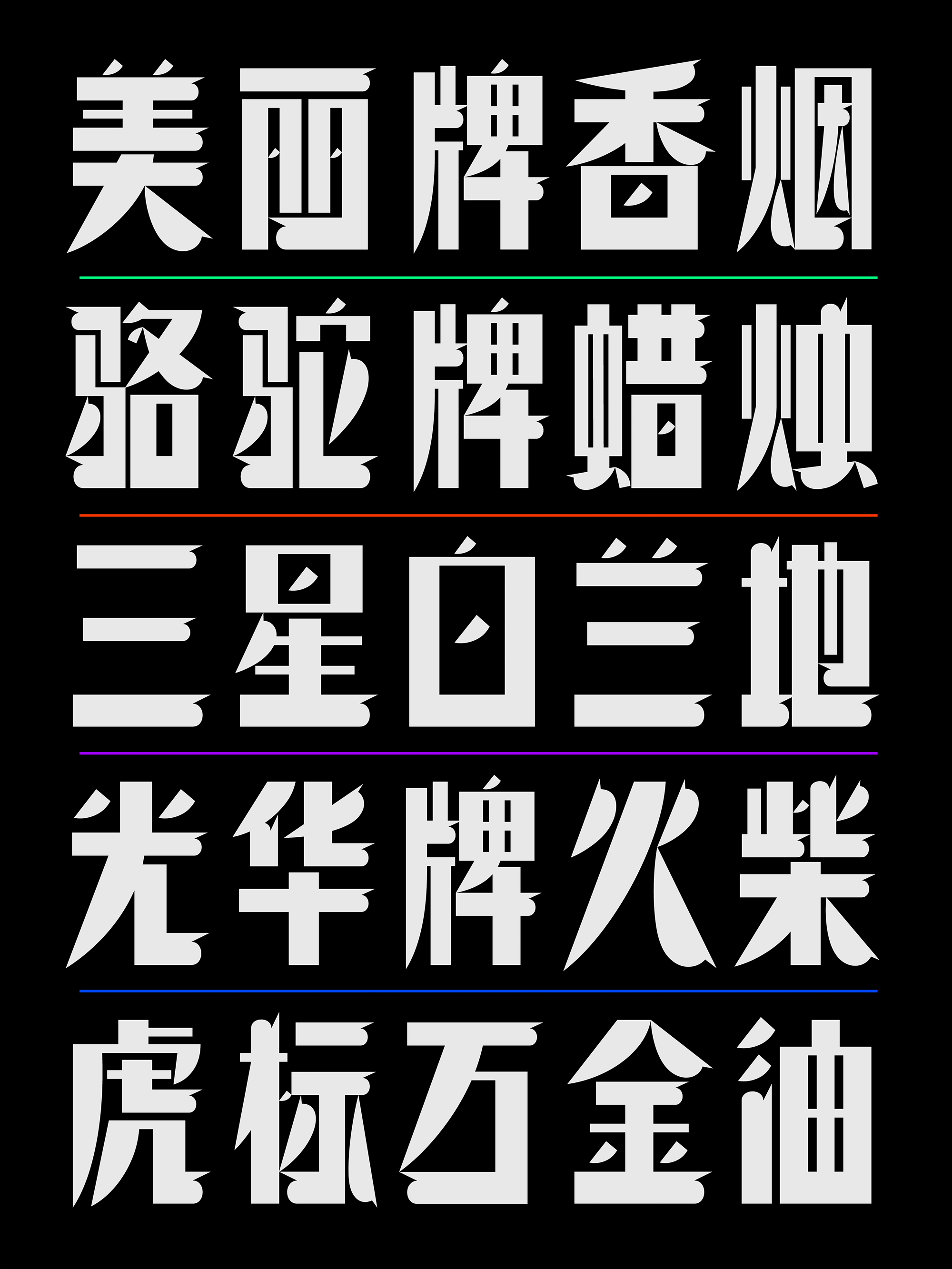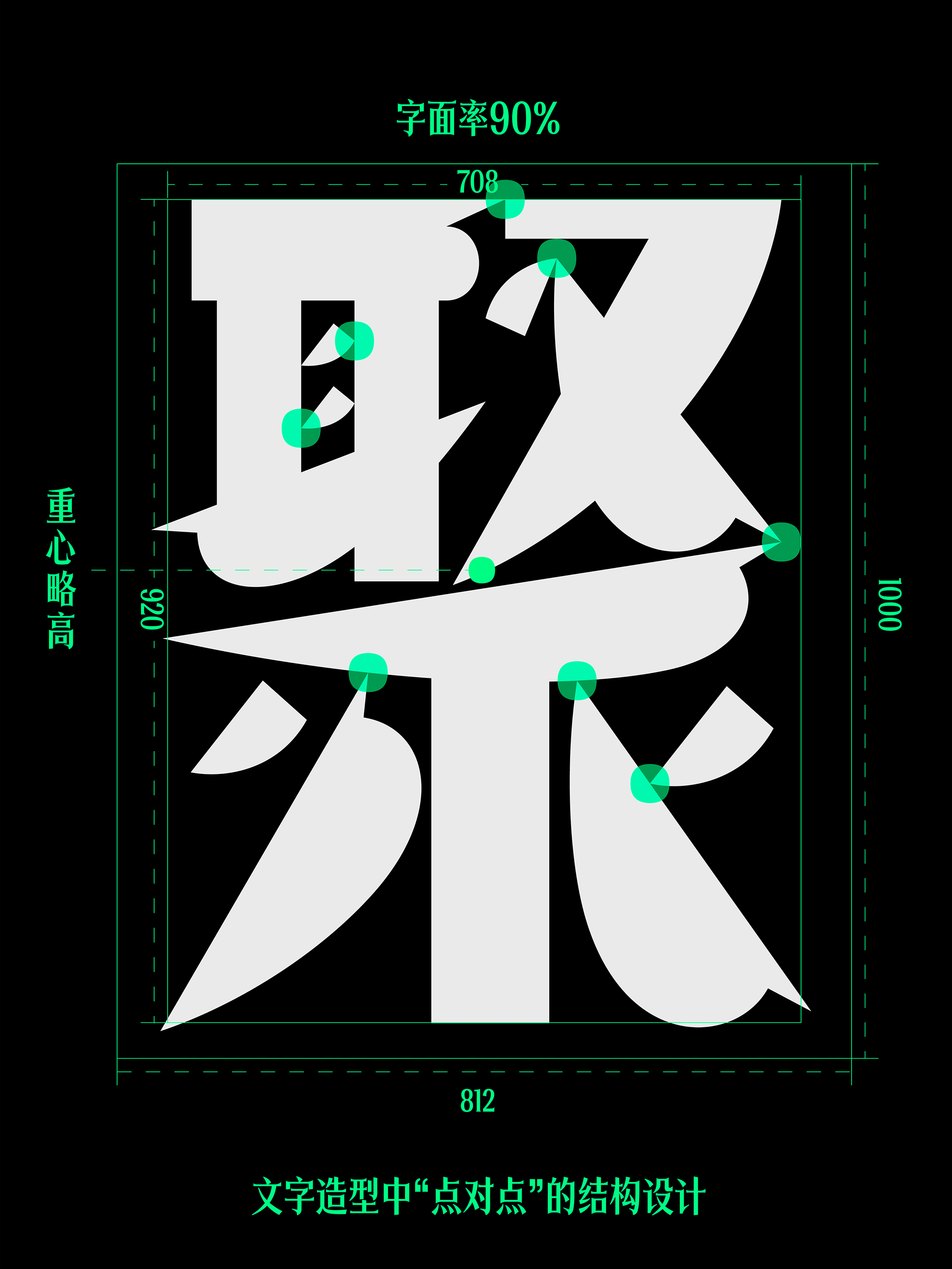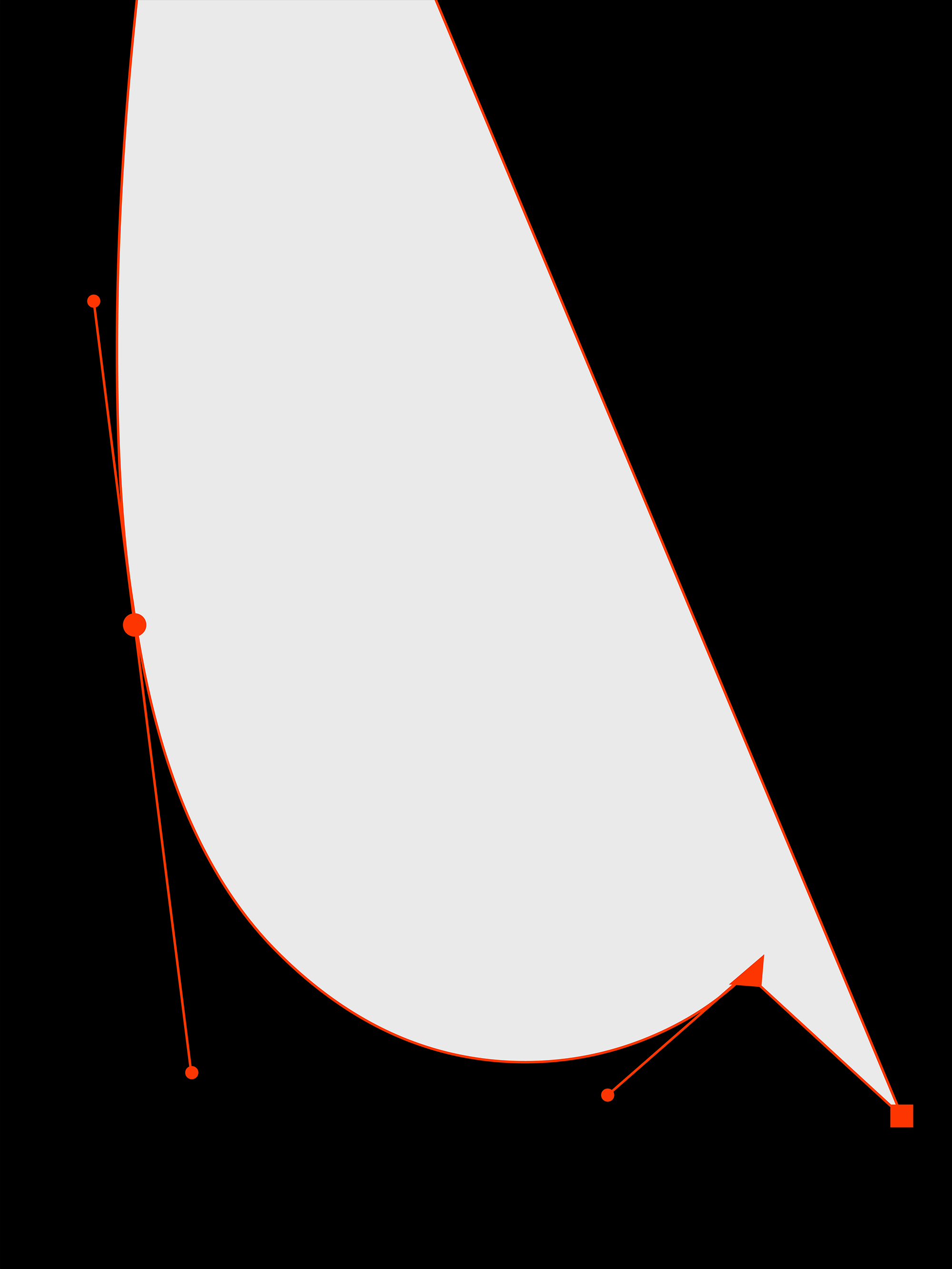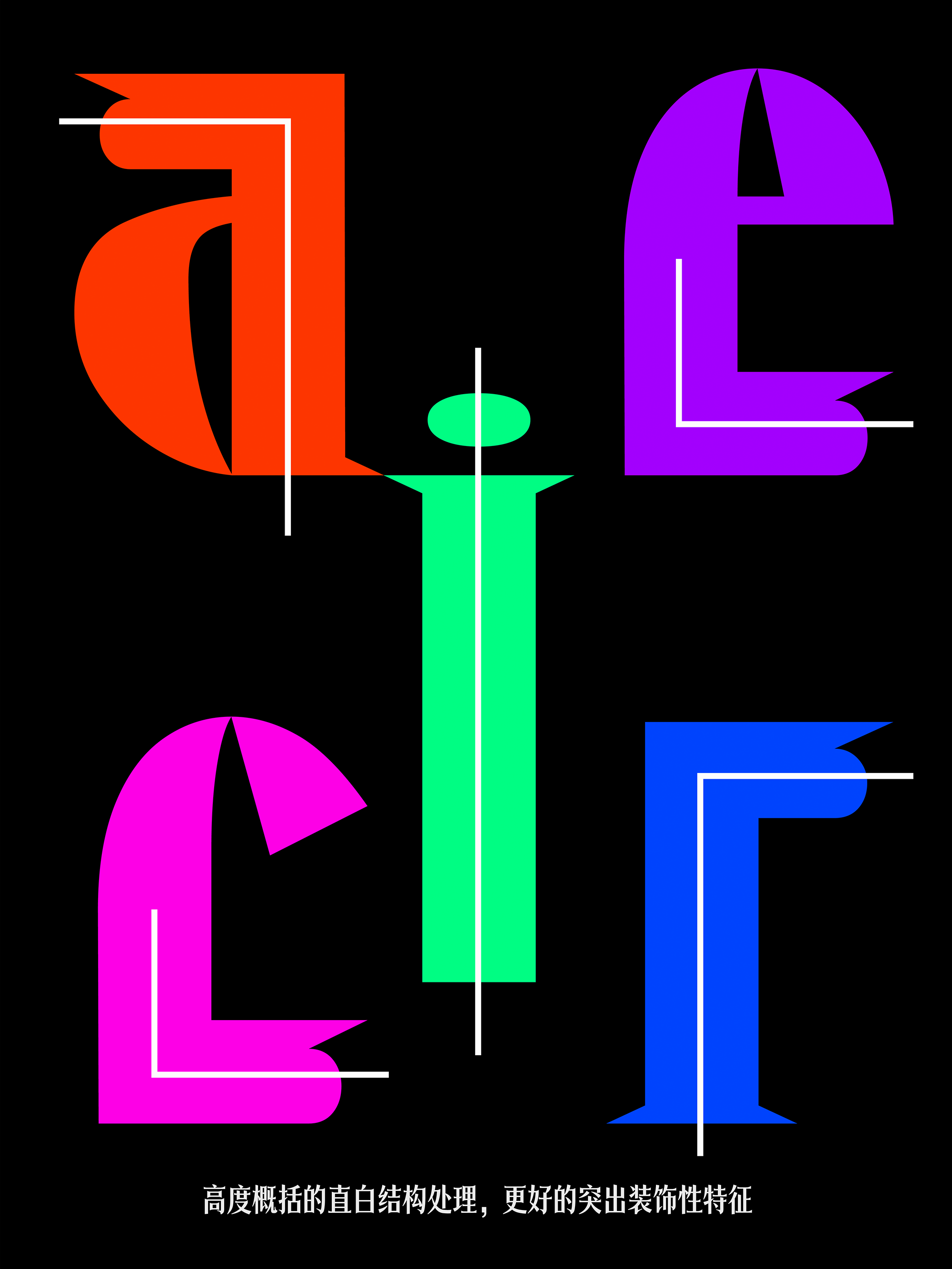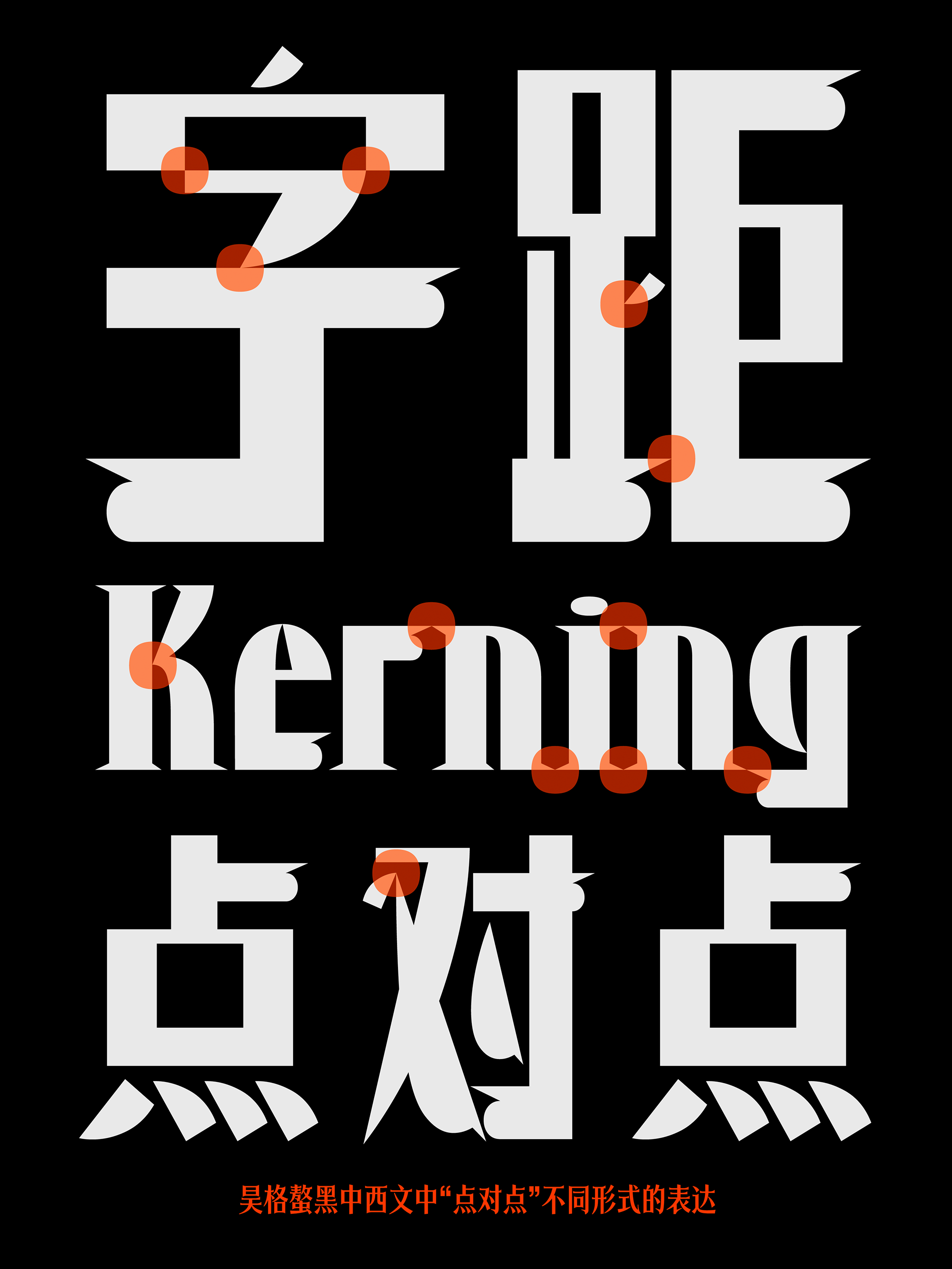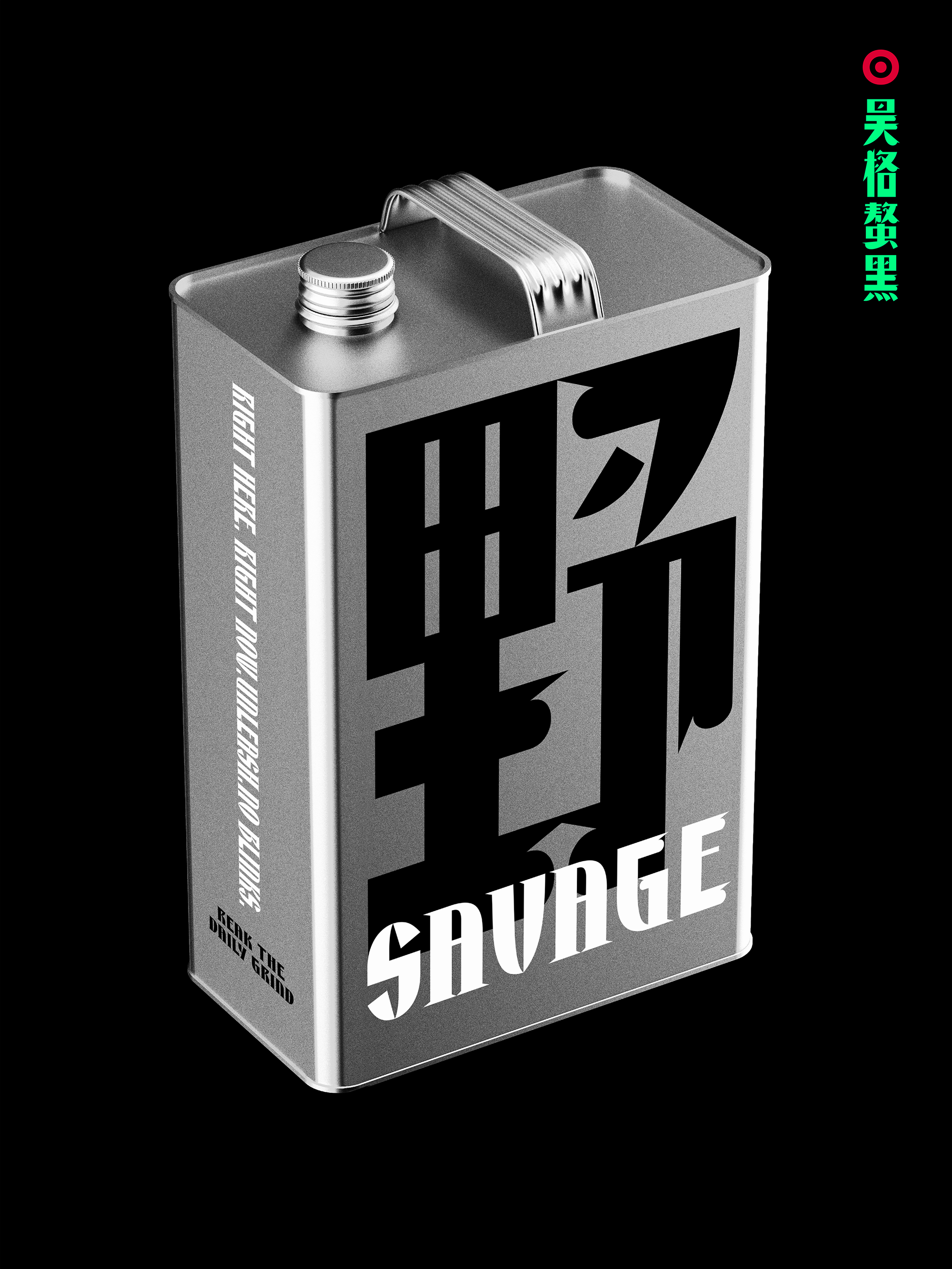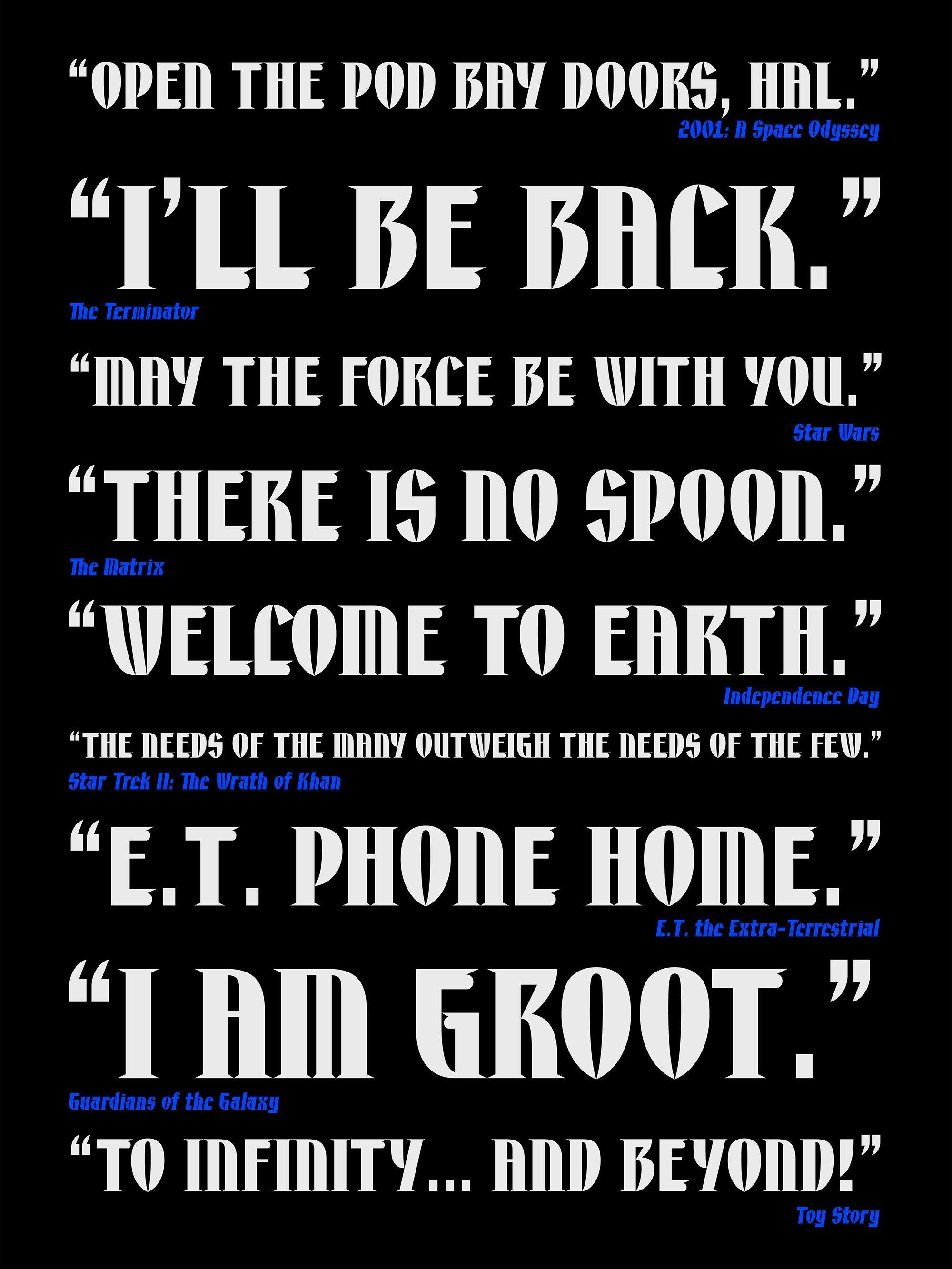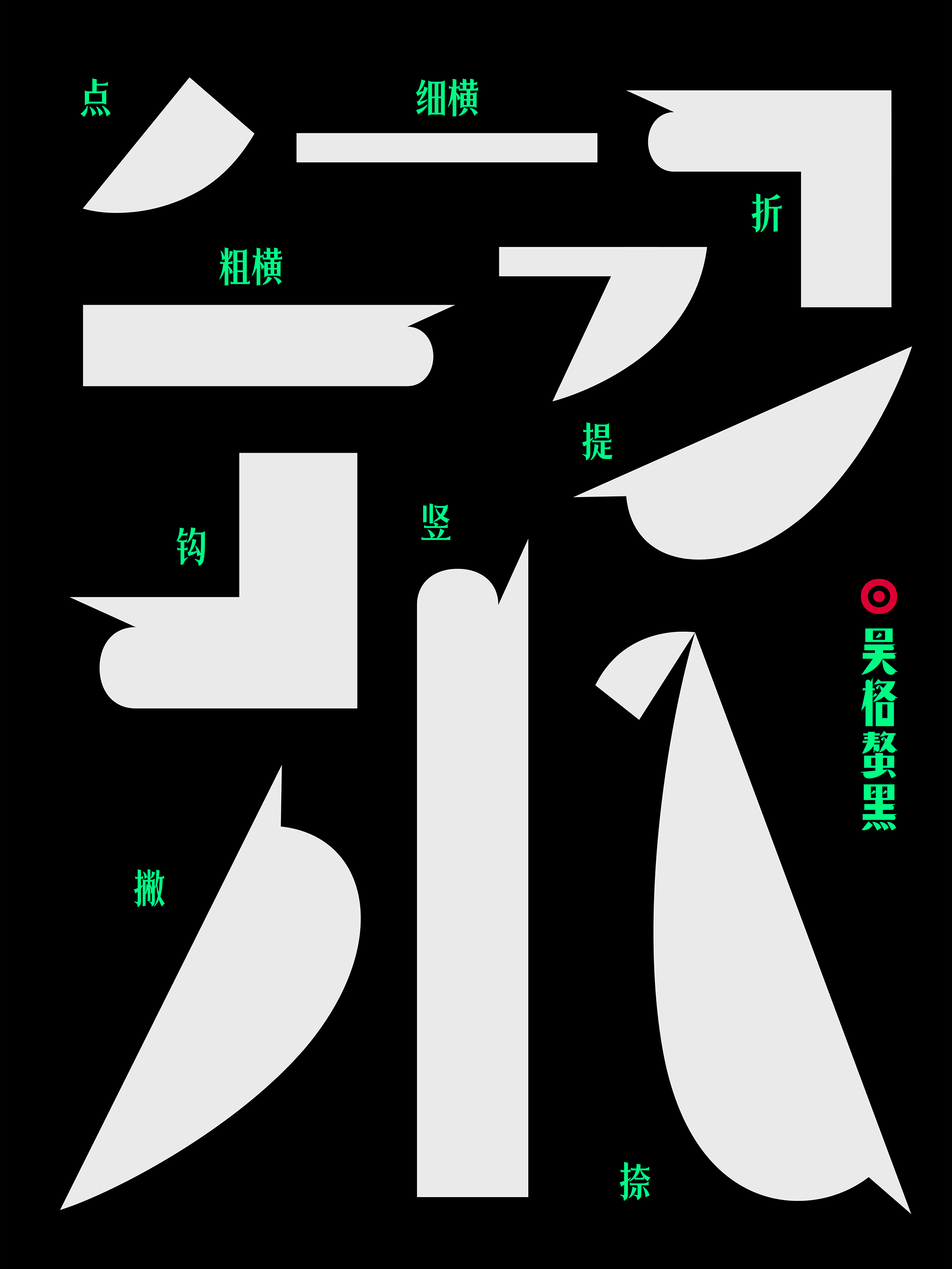
昊格螯黑
昊格螯黑,新发于硎,初露锋芒, 昊格螯黑是一款将民国美术字特征打散重塑的创新黑体。结构上,随笔形灵活变化,打破传统字体统一的字怀、重心、中宫等;笔形上,融入螯刺的造型,以夸张的横竖比,散而不乱的点,带来力透纸背的视觉冲击和张力;细节上,点对点的特征,别具一格,桴鼓相应。
昊格螯黑字体介绍